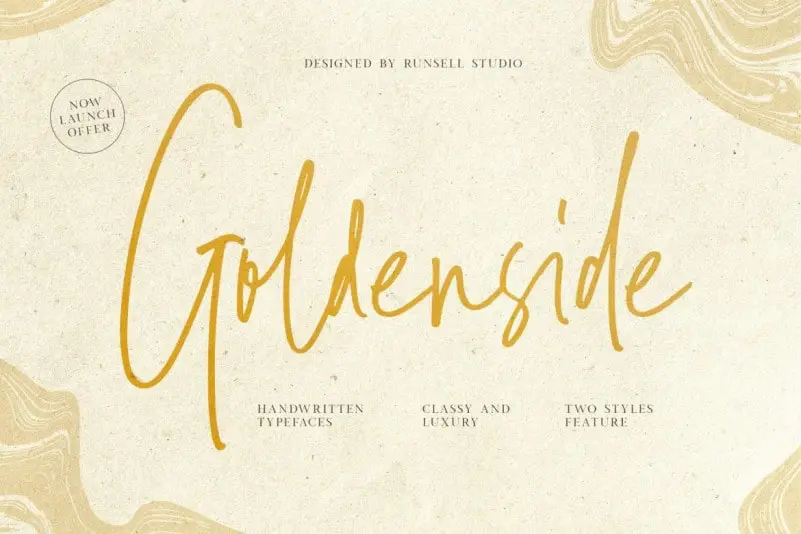
Goldenside Handwriting Font – Fonte Grátis
Goldenside Handwriting Font
Descubra Goldenside Handwriting Font, uma elegante fonte de escrita à mão. Esta tipografia tem uma linha básica dançante que dará ao seu design um toque fresco e moderno. Goldenside é perfeito para projetos autênticos em áreas como marcação, webdesign, revistas, impressão, cerâmica, frases, logotipos, cartões de casamento, embalagens, etiquetas e outras aplicações. Essa fonte foi criada para aqueles que valorizam a autenticidade na design. Com sua curva distintiva e elementos de desenho à mão, você pode criar designs tipográficos impecáveis em um piscar d’olhos — seja para uma marca poderosa ou para frases românticas. Este é o tipo certo para qualquer projeto que valoriza a elegância e a autenticidade da escrita à mão.